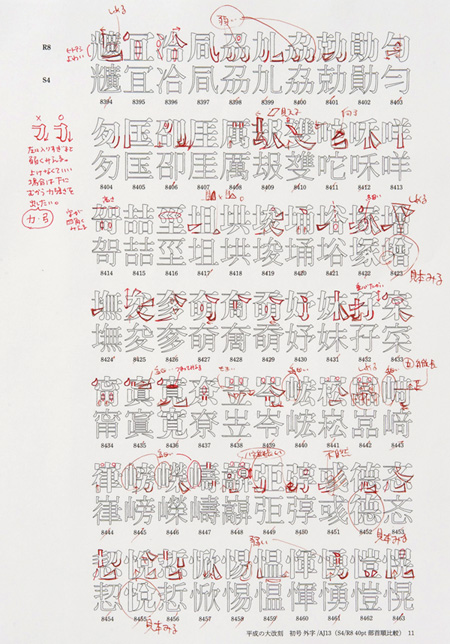
秀英初号の修正指示
三次修整を前に、秀英体開発室が修整ポイントの指示を行った資料。二次修整後の改刻初号(上)とS4初号(昭和四年発行の『明朝初号活字見本帳』の印影)(下)。
細いものはS4初号にない文字。特定の部首などにまとまって指示が集中しているのは、やはりエレメントを統一した影響による。
一〇〇年目の書体づくり 「秀英体 平成の大改刻」の記録 第二章 秀英初号明朝